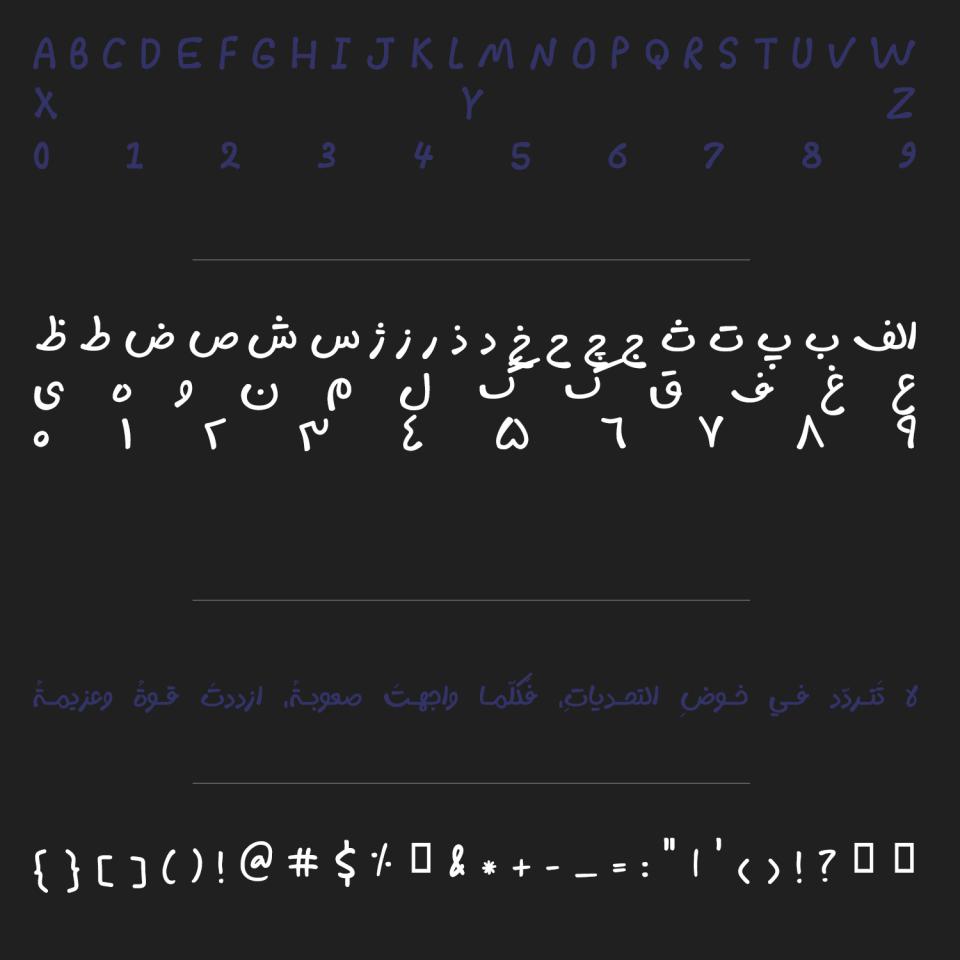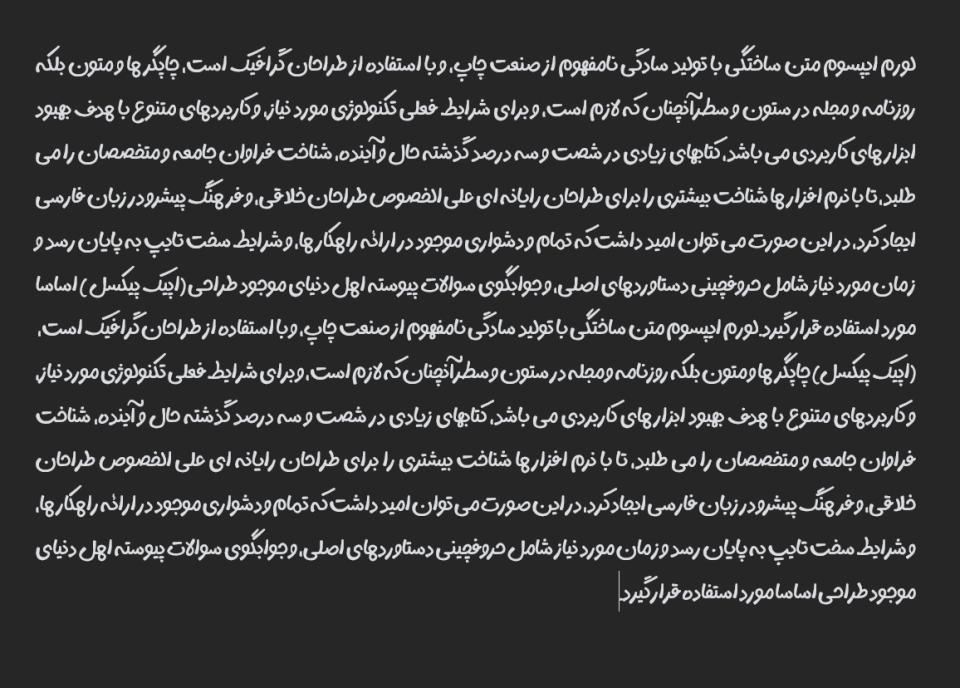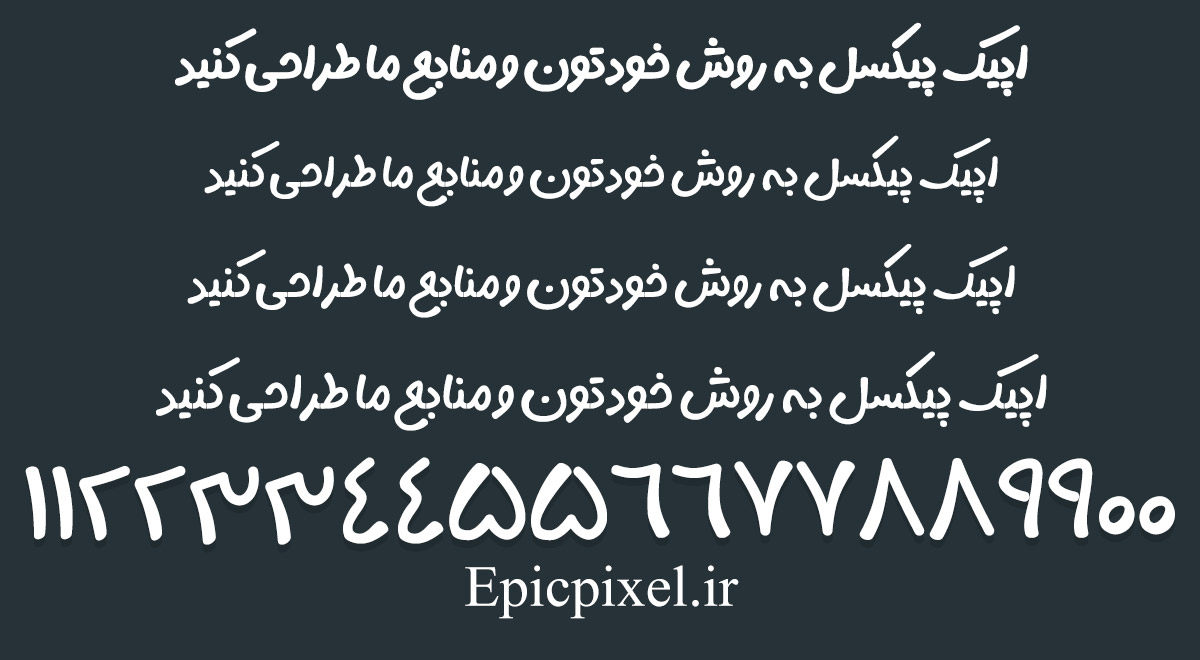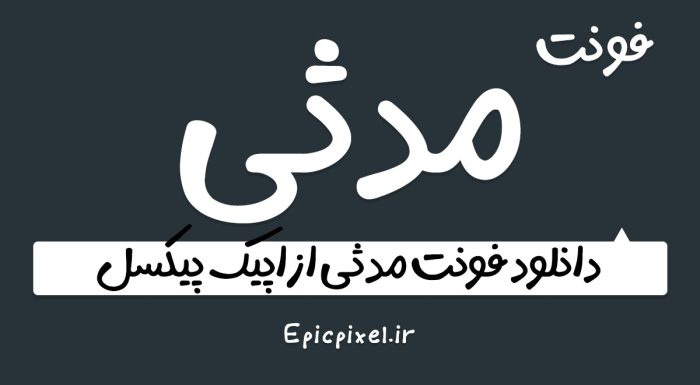
فونت مدثی فارسی Madasi
فونت دست نویس مدثی، یه انتخاب عالی برای کساییه که دنبال یه فونت خاص و متفاوت برای پروژه های گرافیکی شون هستن. این فونت با ساختار ماژیکی و ضخیمش، حس دست نویس بودن رو به خوبی منتقل می کنه و به همین خاطر، برای طراحی عکس نوشته ها، کارت پستال ها، و حتی متن های طولانی تر که می خواین یه حس صمیمی و دوستانه داشته باشن، خیلی مناسبه.
یکی از ویژگی های برجسته مدثی، خوانایی بالای اونه. با وجود ظاهر دست نویس، کلمات به راحتی قابل تشخیص هستن و چشم رو خسته نمی کنن. این ویژگی به خصوص برای استفاده در فضاهای مجازی و وبسایت ها خیلی مهمه، چون کاربر باید بتونه متن رو بدون مشکل بخونه. البته باید این نکته رو هم در نظر داشت که به دلیل ضخامت نسبی، شاید برای متن های خیلی ریز یا جاهایی که فضای محدودی دارین، بهترین گزینه نباشه.
مدثی یه فونت تک وزن هست، یعنی فقط یه حالت ضخامت داره. این می تونه هم یه مزیت باشه و هم یه محدودیت. مزیتش اینه که استفاده ازش خیلی راحته و نیازی نیست نگران انتخاب وزن مناسب باشین. اما از طرف دیگه، انعطاف پذیری کمتری در طراحی بهتون می ده، چون نمی تونین از وزن های مختلف برای ایجاد تنوع بصری استفاده کنین. با این حال، همین تک وزن بودن، به فونت یه انسجام و هماهنگی خاصی بخشیده.
ترکیب هاش اکثرا با همزه هست تست کنین خیلی جذاب میشه مثلا پنج تا ء کنار هم تبدیل میشه به یک شکلک